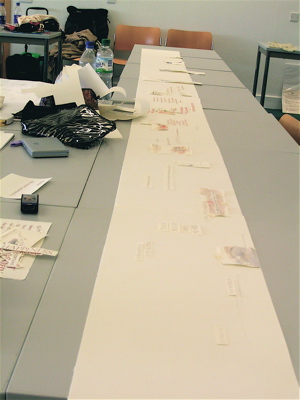
まきもの
今年の夏、イギリスのサンダーランドのシンポジウムに参加し、Ann Heckleのクラスを受講しました。
クラスの内容は、各自のプロジェクトを進めていくのですが、そのプロセスを体験するという内容なので、とても精神的、哲学的です。ディスカッションも非常に多く、英語に付いて行くのに必死
単にグラフィック的に美しい作品を作るのか、それともいつも自己の内面を見つめてそれと対峙してプロセスに身をゆだねるか。それがこのクラスのコンセプトだった様に思います。作品制作のアプローチに関することが主でしたが、今までこういう事を教えてくれるクラスはなかったのでとても勉強になりました。音楽を聴いたり、ヨガ体操をしたり、インスピレーションを得るためにお散歩に行ったり、単にテクニックを教わるという内容ではなく、その点では本当に楽しいものでした。
私はいろいろと進めて行くうちスクロールになりました。時の流れの普遍性を、一日、季節、そして人生として表現した作品を作りたいと思ったので、一瞬一瞬の集まりが時の流れを作 るということを表現するには、スクロールという形がいいだろうということになりました。すべて開いて見るのではなく、両端を丸めてある範囲のみ見て行くムービーの様な 形が合っていると思ったのです。
クラスでは、ドラフト程度を持参することになっていて、私はこんな鉛筆書きの線とマークのイメージとアイデアを持っていきました。
それ以外はすべてクラスの中で発展させていきます。
なんだか、イメージから離れて行く様な・・・。書体なのか、色なのか。
イメージは結局鉛筆と水彩絵の具でシンプルにすることにして、あとは文字とイメージと見て行くスピードやペース、そしてテキストの内容がポイントです。
最初からゴールをみつめないという考え方は、新たな道を見いだすきっかけを作りました。
当初は苦しい作業になるのかと心配しましたが、時間をかけて考えたり作業したりするプロセスは以外と心地良く、様々なことに影響し合う小さな変化をみつけて大事にする、ということがいかに大切かということがよくわかりました。
瓦に書く人、曼荼羅を作る人、墨絵風の作品、写真とのコラボ作品、女性の生き方を美しい貝がらとともに表現する人、ケルズの書に出て来る猫の話などなど、取りかかっていた物は人それぞれでしたが、結局クラスの誰も完成する人はいませんでした。
しかし、それぞれが実のある体験をした素晴らしいクラスでした。
Sheila Watersの著書"Foundations of Calligraphy"の中のFROM CONCEPTION TO COMPLETIONの章でThere is never a single answer to a layout problem.と書いてありますがSさんがなさって来られたことが「まさにこれかあ〜」と思いました!
Sheilaのお言葉には重みがありますね。まさにその通りだと思います。Sunderlandで彼女にお会いしましたが、とてもお元気そうでした。
何かを決定するときには、自分のを心(自分でも気がつかない小さな声)に耳をすませて、それを大事にしなさい、いつも必ず自分の気持ちに立ち戻りなさいとAnnも言ってました。
無意識な自分の心が、その時々の問題点を決めているのかもしれません。
何かを解決するときには、それにゆだねることが結果的に多くの解決策につながっていくのだと思います。